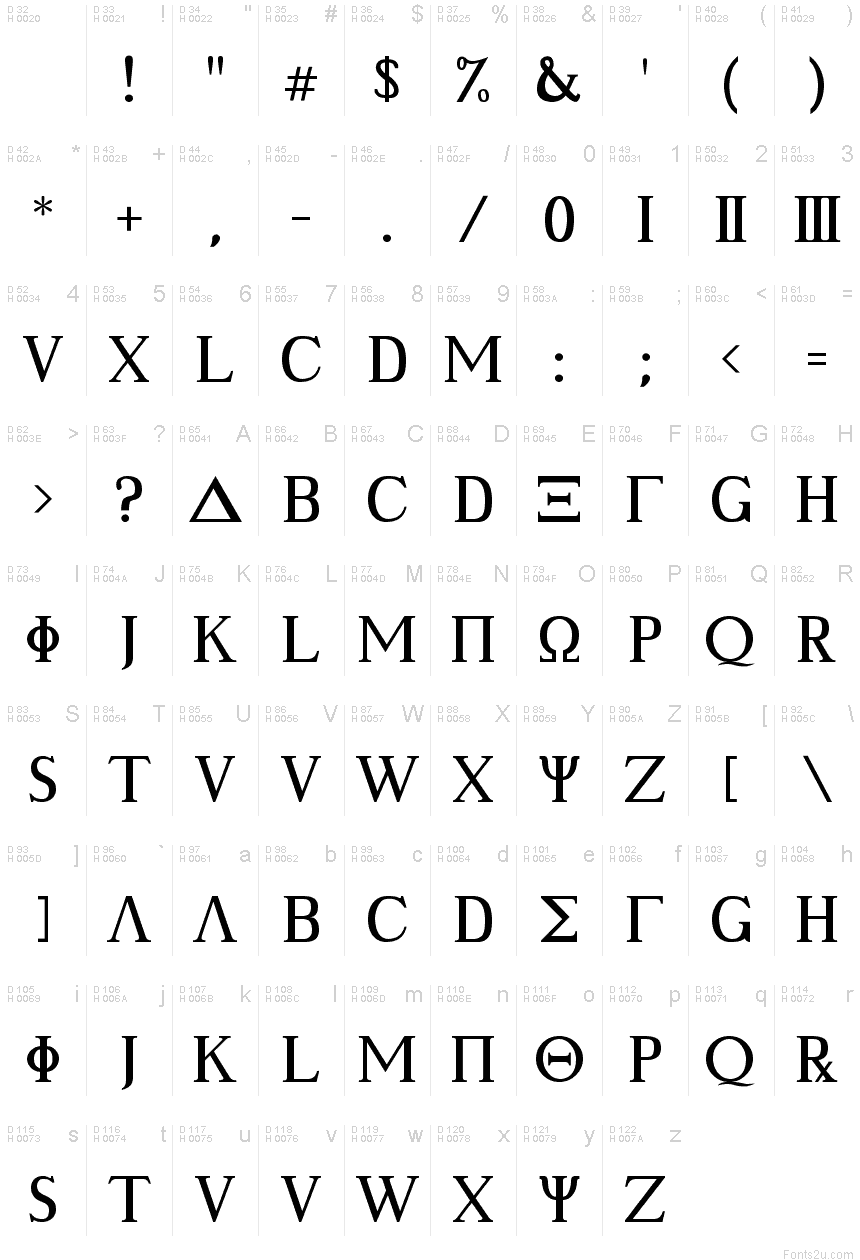
Krój pisma Ancient Geek autorstwa Matthew Welcha to darmowy, dekoracyjny font inspirowany greką, który oddaje śmiały, ciosany w kamieniu charakter dawnych inskrypcji. Kanciaste litery, proste cięcia i masywne kreski wyglądają, jakby zostały wyryte w marmurze, nadając tekstowi wyrazistą, niemal ceremonialną formę. Zwarte tempo i czysta geometria sprawiają, że font pozostaje czytelny nawet w dużych rozmiarach, dzięki czemu nagłówki wyglądają na mocne i uporządkowane, a nie chaotyczne.
Dzięki Ancient Geek nadasz mityczny klimat plakatom, tytułom gier, wydarzeniom studenckim, grafikom bractw, koszulkom czy zaproszeniom na imprezy tematyczne. Ten darmowy font sprawdza się najlepiej, gdy jest użyty w dużej skali i ma przestrzeń, by wybrzmieć. W tekście głównym warto połączyć go z prostym, nowoczesnym krojem bezszeryfowym, aby zachować czytelność i spójność wizualną.
Font przypisuje greckie glify do liter łacińskich na podstawie podobieństwa wizualnego, a nie wartości fonetycznej.
Litery greckie, które nie miały wizualnego odpowiednika w alfabecie łacińskim, zostały pominięte, a pozostałe miejsca wypełniono standardowym alfabetem łacińskim.
W rezultacie, wpisując tekst łaciński, uzyskujesz wynik, który wygląda jak greka, pozostając przy tym w pełni czytelnym językiem angielskim.